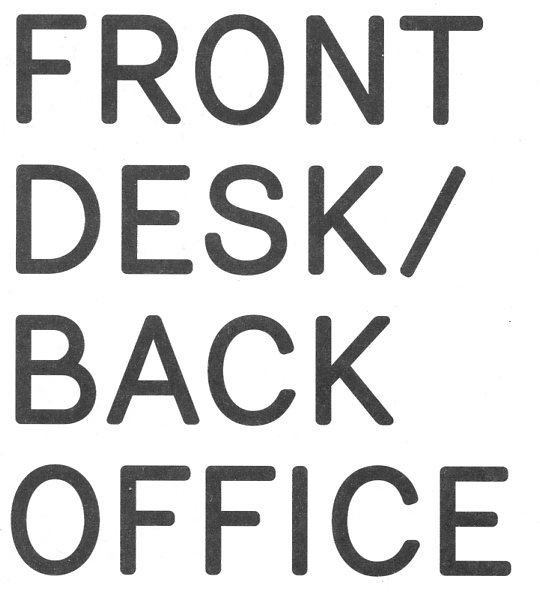
Kennt jemand die Schrift, oder irgendwas in die Richtung?
Das "B" ist besonders, und auch die abgerundeten Ecken ..
Wie immer die Frage: Woher stammt das?
Es handelt sich um ein Buch mit diesem Titel. "Front Desk/ Back Office. The secret of galleries in 39 pictures and two texts". Fucking Good Art edition no. 2, Rotterdam, 2012.
Der Designer hat aber leider nicht die Schrift ins Impressum geschrieben, die er verwendet hat.